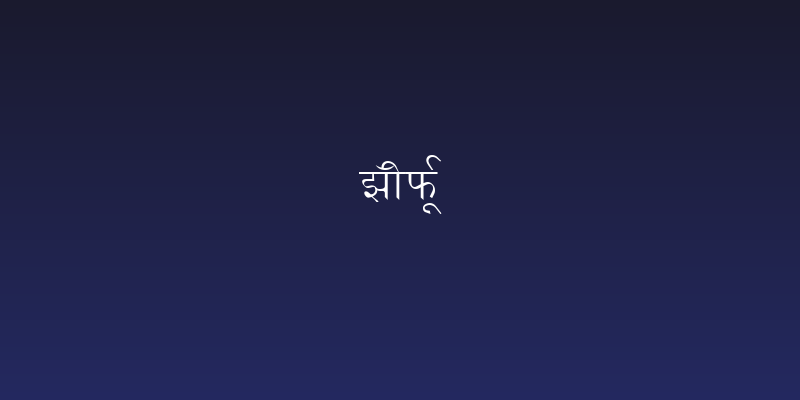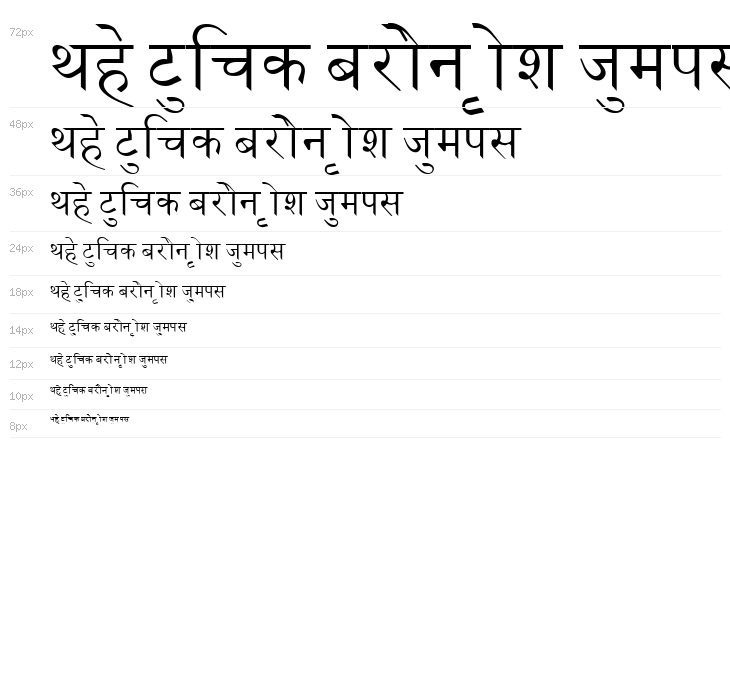
Jaipur Font
| Kategorien | Asian |
| Gesamtstil | Classic |
| Anwendungsfall | Headlines, Body text |
| Vorgeschlagene Projekte | Ideal for cultural publications, educational materials, and traditional event invitations. |